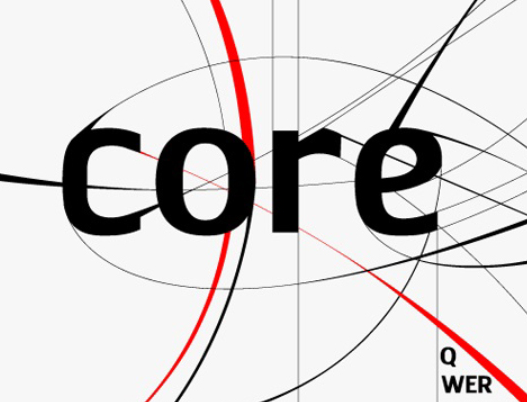
A Core Typeface é uma elegante fonte geométrica sem serif, criada pelo talentoso designer Hamilton. Esta famosa fonte fortemente sólida e desejável traz um toque de personalidade com os traços das letras cortados de forma característica. É perfeita para aplicações que exigem impacto visual como posters, logotipos ou até mesmo roupas estampadas. Perfeito para títulos chamativos e conteúdo ilustrativo, a Core Typeface tem o poder de dar destaque ao seu design, tornando-a uma opção valiosa para qualquer designer interessado em criar um layout único e impactante no Brasil.